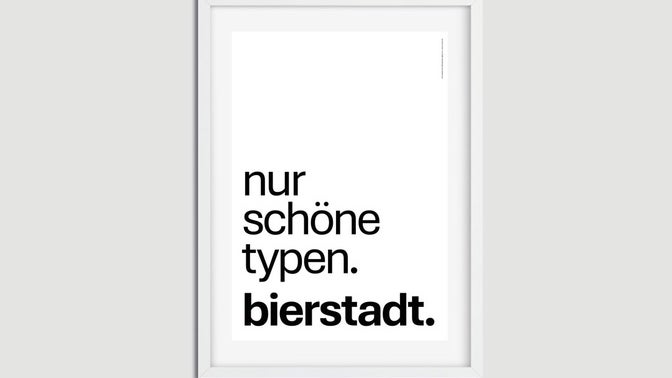
Wie Microsoft beinahe einen deutschen Stadtteil berühmt gemacht hätte
Werbeposter der Bierstadt-Kampagne. (Bild: Q Kreativgesellschaft)
Nach 16 Jahren und mehrjähriger Suche ersetzt Microsoft die Standardschriftart Calibri in allen Office-Anwendungen durch Aptos. Dabei handelt es sich um eine serifenlose Schriftart. Sie orientiert sich, ähnlich wie Helvetica, optisch an der schweizerischen Typografie der Mitte des 20. Jahrhunderts.
Einer ihrer großen Vorteile gegenüber Calibri: Ein kleines L lässt sich hier besser von einem großen I unterscheiden. Optimierungen gibt es auch bei der Lesbarkeit der kleinen Versionen der Buchstaben I und J.
Mit der Entscheidung für Aptos hätte beinahe ein Stadtteil der deutschen Stadt Wiesbaden weltberühmt werden können, wie die Hessenschau berichtet. Denn Aptos hieß vorher Bierstadt – und hatte sich in einer weltweiten Abstimmung von Microsoft-Nutzer:innen gegen Tenorite, Seaford, Skeena und Grandview durchgesetzt.
Freilich hatte Schriftdesigner Steve Matteson nicht den hessischen Stadtteil im Sinn, als er seiner Neuentwicklung den Namen Bierstadt gab. Vielmehr trägt auch ein Gipfel in den Rocky Mountains diesen Namen. Und dieser ist nicht nach Bierstadt in Hessen, sondern nach einem deutschen Maler benannt.
Das hielt allerdings den Typografiefan und Designer der Wiesbadener Werbeagentur Q Thilo von Debschitz nicht davon ab, eine Kampagne zu starten. Brötchentüten, Tassen, Jutebeutel, Fußmatten und T-Shirts wurden laut Hessenschau mit Slogans wie „nur schöne typen. bierstadt.“ bedruckt.
Tatsächlich fiel die Entscheidung der Microsoft-Community auf Bierstadt – allerdings mit einer für Wiesbaden und die Q-Kampagne großen Änderung. Denn Matteson hatte sich dafür entschieden, Bierstadt in Aptos umzubenennen. Letztere ist eine kalifornische Stadt, in der Matteson gern im Urlaub weilt.
Warum, ist nicht bekannt. Designer von Debschitz vermutet, dass vielleicht das Wort „Bier“ im Namen als bedenklich erachtet wurde. Vielleicht ist Bierstadt aber auch für eine weltweite Verbreitung kein allzu geeigneter Name.
Ein kleiner Trost für Bierstadt-Fans: Die Schriftart lässt sich noch immer unter dem alten Namen im Drop-Down-Menü, etwa bei Windows, auswählen. Und: Die Werbeagentur Q will die Bierstadt-Produkte vorerst nicht aus dem Sortiment nehmen.